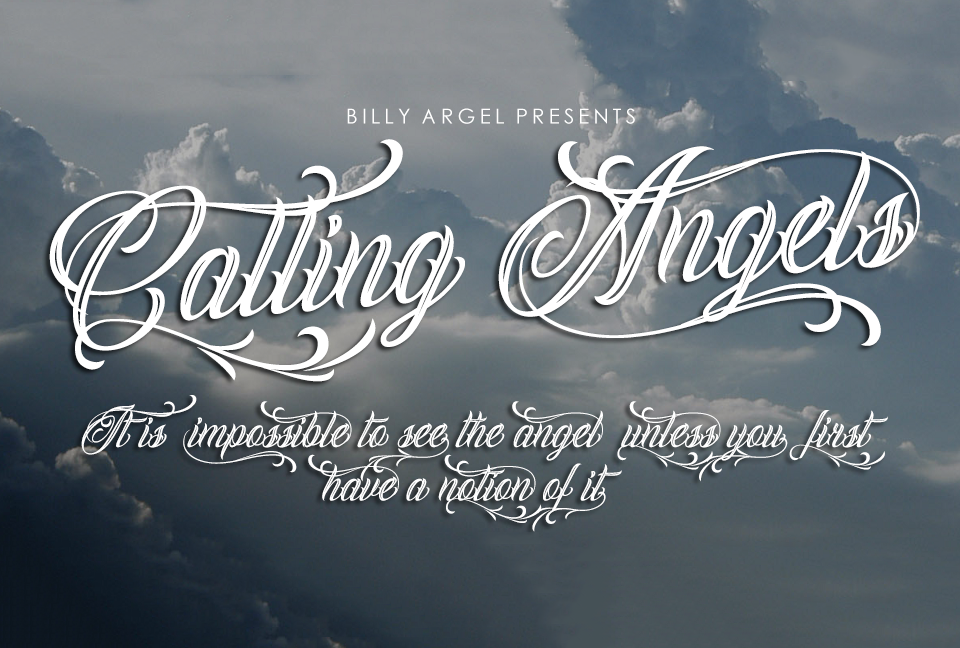
Esta fonte é perfeita para quem procura algo único e moderno para projetos pessoais ou iniciativas locais. Designada como ‘Calling Angels’, ela oferece uma aparência dinâmica e desafiadora, certamente atraente para um design de display em websites ou impressões digitais. Essa fonte está disponível tanto na versão gratuita quanto na comercial, dependendo da necessidade específica do seu projeto. O designer Billy Argel criou esta fonte com uma característica única: possui ligaturas deslizantes que permitem diferentes combinações de caracteres e são usadas principalmente para fins estéticos. As ligações não estão fusas em letras como na versão gratuita, o que as torna mais complexas e atraentes visualmente. A disponibilidade completa da fonte inclui também swashes livres – essencialmente letras curvadas adicionadas ao final de uma palavra para dar um toque elegante. Estes detalhes tornam ‘Calling Angels’ ainda mais divertido para adicionar em suas próximas criações, independentemente do tamanho ou formato de seu projeto. A fonte é ideal para designers que buscam algo diferente e interessante, sem comprometer a legibilidade. Se você está buscando uma fonte que se destaca no meio da multidão, ‘Calling Angels’ pode ser o ajuste perfeito. Para obter mais detalhes ou informações sobre as versões comerciais disponíveis, visite os sites de Billy Argel na internet.